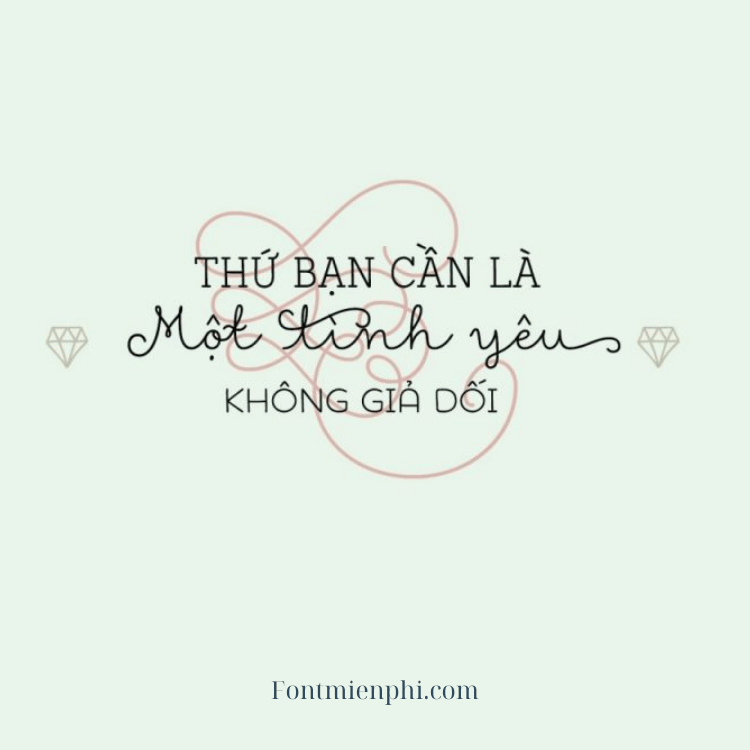
Việt hóa font iCiel Showcase
Việt hóa font iCiel Showcase: Bộ font phong cách cổ điển dành cho thiết kế
Sự độc đáo của việc Việt hóa font iCiel Showcase
Nếu bạn đang tìm kiếm một công cụ để nâng tầm dự án thiết kế của mình, việc Việt hóa font iCiel Showcase chính là lựa chọn hoàn hảo nhất. Đây là một bộ Font Miễn Phí mang đậm phong cách vintage và cổ điển, rất phù hợp cho những ai muốn tạo ra những tác phẩm có tính nghệ thuật cao. Showcase không chỉ đơn thuần là một kiểu chữ, nó còn là sự kết hợp giữa nét viết tay tinh tế và các đường nét bo tròn mềm mại, tạo cảm giác thân thiện nhưng vẫn vô cùng sang trọng.
Đặc điểm nổi bật của bộ font iCiel Showcase
Bộ font này bao gồm nhiều kiểu dáng đa dạng từ nét thanh, nét đậm đến các ký tự trang trí bắt mắt. Khi được Việt hóa, iCiel Showcase đã khắc phục hoàn toàn lỗi hiển thị tiếng Việt, giúp người dùng dễ dàng gõ các dấu câu một cách chuẩn xác mà không làm mất đi tính thẩm mỹ ban đầu của bộ thiết kế gốc. Sự linh hoạt của nó giúp bạn ứng dụng tốt trong nhiều bối cảnh khác nhau.
Ứng dụng thực tế của Việt hóa font iCiel Showcase
Các nhà thiết kế thường sử dụng font iCiel Showcase cho các loại bao bì sản phẩm, thiệp mời đám cưới hoặc bìa sách. Với vẻ ngoài độc bản, nó giúp tiêu đề trở nên nổi bật và thu hút sự chú ý ngay lập tức. Ngoài ra, iCiel Showcase còn rất được ưa chuộng trong việc tạo nội dung truyền thông xã hội nhờ khả năng biểu đạt cảm xúc tốt thông qua các đường cong uyển chuyển.
Kết luận về bộ font Việt hóa iCiel Showcase